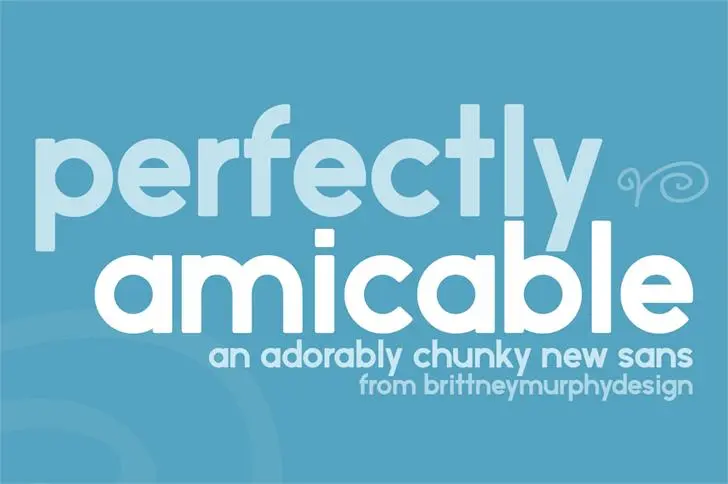
Perfectly Amicable Font
A Perfectly Amicable Font é uma elegante fonte sans-serif que trouxe tranquilidade para os designers brasileiros há alguns anos, criada por Brittney Murphy Design no ano de 2016. Inspirada na simplicidade e harmonia do nosso país, essa fonte se destaca pela sua proporção perfeita, facilidade de leitura e modernidade que a torna perfeita para diversos projetos gráficos tanto em negócios quanto em design editorial. A Hamilton Design Team adotou-a como parte fundamental da sua paleta de fontes, reconhecendo suas qualidades únicas e versáteis. Ideal tanto para materiais digitais quanto impressos, a Perfectly Amicable é uma escolha ótima para garantir um resultado profissional e agradável para seus projetos.